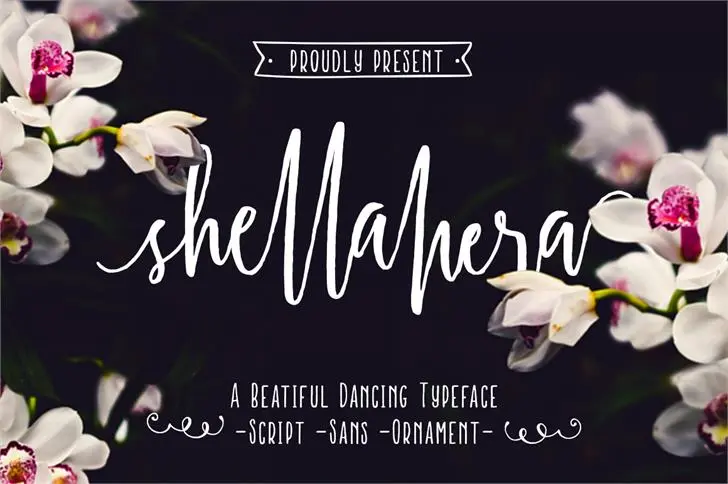
A ShellaheraScript é uma elegante fóntes de escritura que foi criada pela Hamilton em 2016. Este estilo especializado em calligrafia oferece um charme único e uma profundidade única, tornando-o perfeito para anúncios de marca, design gráfico e decoração de casamentos tradicionais. Suas linhas fluidas e detalhes elaborados dão ao texto um toque refinado que se destaca em qualquer projeto, seja ele online ou impresso. Esta fonte é uma escolha ótima para aqueles que buscam estilizar seus trabalhos com uma dose de personalidade única.